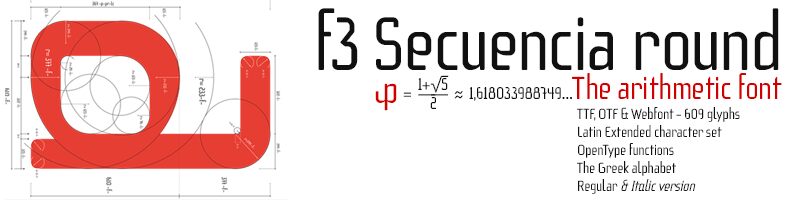
f3 Secuencia round ffp
Esta fuente se basa en sus proporciones, en la sucesión de fibonacci, la secuencia de Lucas y el triangulo de Kepler. Soy deFharo freelance en Spain, visita mi web defharo.com